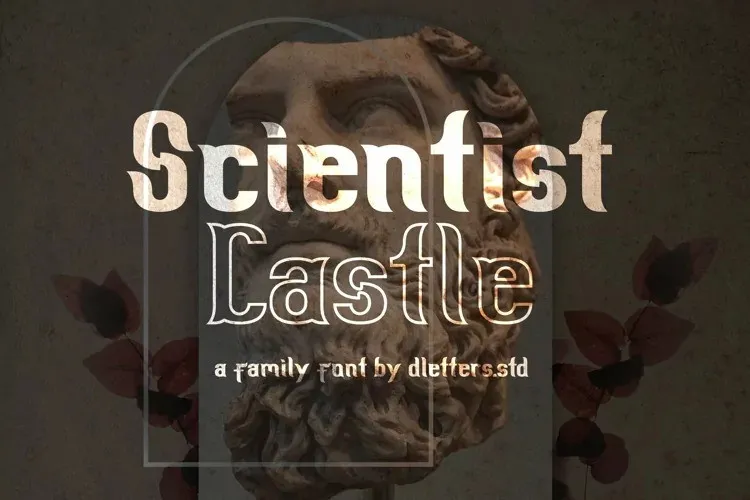
Scientist Castle Font – Download Grátis
Esta fonte tipo, chamada ‘Scientist Castle’, foi cuidadosamente criada para inspirar-se nas designs e ilustrações urbanas. Inspirado nos estilos presentes nas cidades, ela está disponível em quatro estilos distintos que você pode usar conforme apropriado, como uma combinação de separação baseada no estilo do design. A fonte conta com recursos OpenType que permitem-lhe dar um aspecto mais calligraficamente interessante! E contém as seguintes estilos: regular, itálico, efeito efeito itálico. Estes estilos são muito fáceis de usar, sem mencionar a facilidade para aplicar um toque urbanizado à sua própria design ou marca. Ela é perfeita para quem procura uma fonte que expressa o espírito vibrante das cidades e deseja dar um tom especial ao seu projeto. Com o ‘Scientist Castle’, você tem a possibilidade de criar designs únicos, com uma aparência moderna e arquitetônica, que se encaixam perfeitamente em qualquer contexto de design. Não hesite em explorar as opções disponíveis desta fonte, para tornar seu próximo projeto ainda mais impactante.